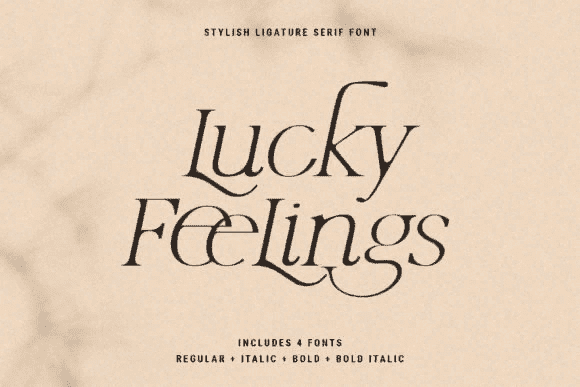
[Creativefabrica] Lucky Feelings Font (2021)
Название: Lucky Feelings Font (2021)
[Creativefabrica] Lucky Feelings Font (2021)
ucky Feelings - это тонкий и изящный шрифт с засечками.
Влюбитесь в его восхитительный стиль и используйте его для создания великолепных свадебных приглашений, красивых канцелярских товаров, привлекательных постов в социальных сетях и многого другого!